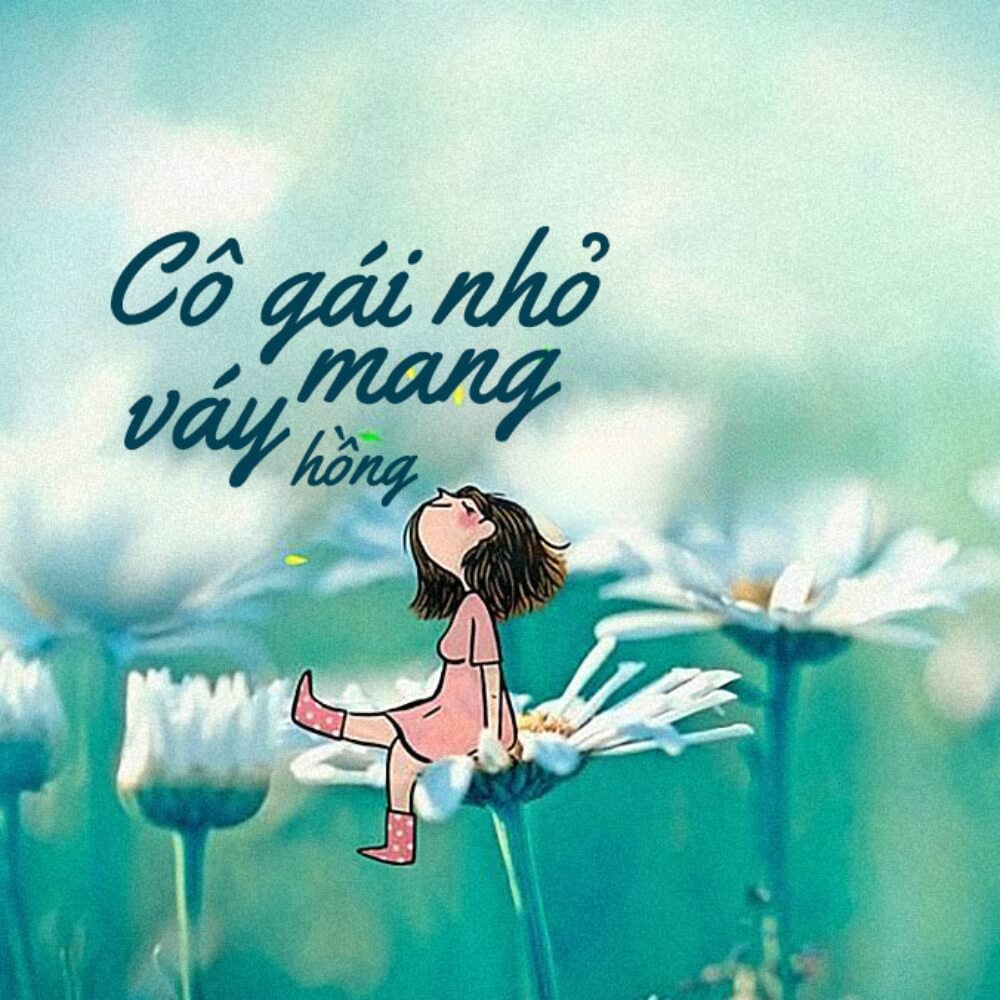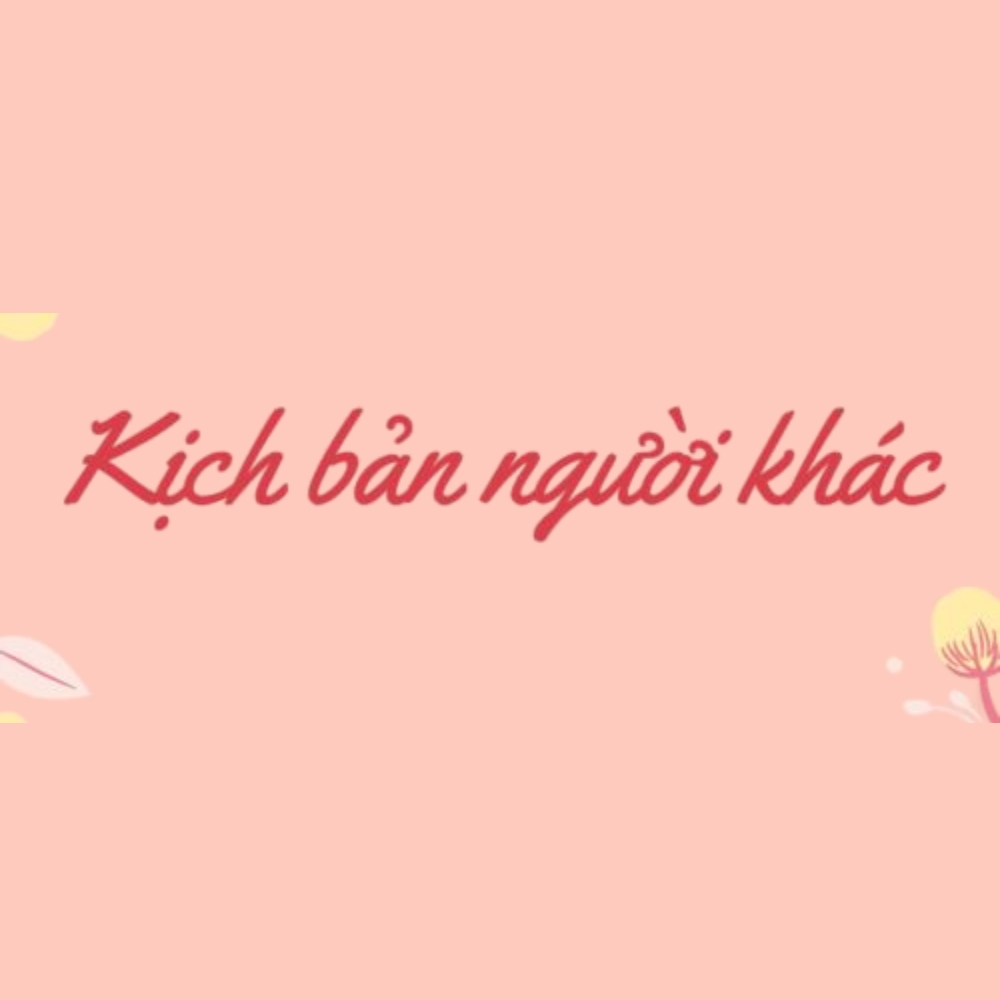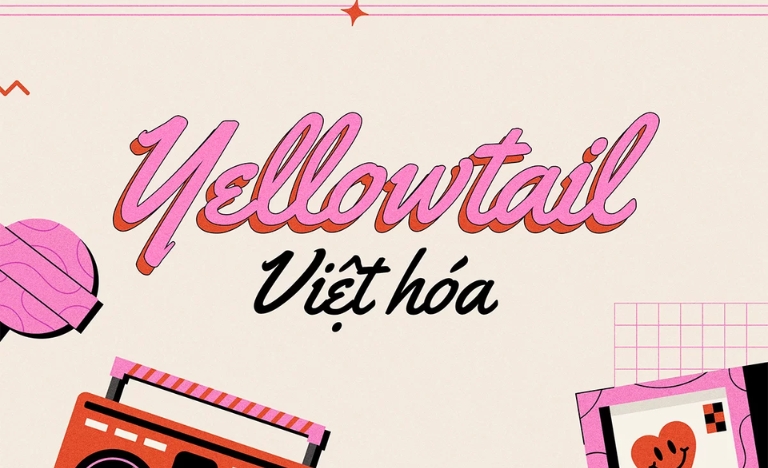
Không ít người khi tìm font Việt hóa Yellowtail thường gặp tình trạng tải về nhưng chữ bị lỗi dấu, thiếu ký tự tiếng Việt hoặc font không hiển thị đúng trong phần mềm thiết kế. Một số file chia sẻ trên internet chỉ là phiên bản chưa việt hóa hoàn chỉnh nên khi sử dụng trong logo, poster hay banner rất dễ bị sai bố cục chữ.
Điều này khiến thiết kế mất đi sự tinh tế và chuyên nghiệp. Trong bài viết này, xưởng In Viva chia sẻ bộ font việt hóa Yellowtail đầy đủ giúp bạn sử dụng dễ dàng cho thiết kế và in ấn.
Trước khi tải font về sử dụng, bạn nên kiểm tra kỹ định dạng file và khả năng hỗ trợ tiếng Việt. Điều này giúp font hoạt động ổn định trên các phần mềm thiết kế phổ biến như Illustrator, Photoshop hoặc CorelDRAW. Dưới đây là thông tin cơ bản của bộ font việt hóa Yellowtail.
| Tên font | Yellowtail |
| Kiểu chữ | Script / Handwriting |
| Hỗ trợ | Tiếng Việt đầy đủ |
| Ứng dụng | Logo, poster, banner, typography |
Bộ font lnth yellowtail việt hóa thường được sử dụng trong các thiết kế mang phong cách chữ viết tay hiện đại. Nhờ nét chữ mềm mại, font này dễ tạo cảm giác tự nhiên và thân thiện trong nhiều loại ấn phẩm.
Đặc điểm nổi bật của font việt hóa Yellowtail
Trong nhóm font script, font việt hóa Yellowtail được nhiều designer lựa chọn nhờ phong cách chữ viết tay thanh thoát và dễ ứng dụng. Khác với nhiều font calligraphy phức tạp, Yellowtail có cấu trúc chữ rõ ràng nên vẫn giữ được tính thẩm mỹ nhưng không gây khó đọc.
Những đặc điểm nổi bật của font việt hóa lnth Yellowtail gồm:
- Nét chữ mềm mại và tự nhiên giống chữ viết tay.
- Khoảng cách chữ hợp lý giúp dễ đọc hơn so với nhiều font script khác.
- Phù hợp cho thiết kế logo, tiêu đề hoặc typography.
- Dễ kết hợp với nhiều font sans-serif trong bố cục thiết kế.
Nhờ những ưu điểm này, tải font chữ lnth yellowtail việt hóa đang trở thành lựa chọn phổ biến với designer khi thiết kế poster hoặc thương hiệu mang phong cách trẻ trung.
Ứng dụng font Yellowtail trong thiết kế và in ấn
Nhờ phong cách chữ viết tay mềm mại, font việt hóa Yellowtail có thể ứng dụng linh hoạt trong nhiều lĩnh vực thiết kế khác nhau. Khi sử dụng đúng cách, font này giúp tạo điểm nhấn tinh tế cho tiêu đề hoặc logo.
Một số ứng dụng phổ biến của font này gồm:
- Thiết kế logo: nhiều thương hiệu sử dụng font script để tạo cảm giác thân thiện và cá tính.
- Poster sự kiện: font Yellowtail giúp tiêu đề nổi bật và thu hút người xem.
- Banner quảng cáo: nét chữ mềm mại giúp tạo cảm giác gần gũi.
- Typography: thường dùng trong các thiết kế quote hoặc artwork.
Trong thực tế, nhiều designer thường kết hợp font việt hóa Yellowtail với font sans-serif để tạo sự cân bằng giữa tính nghệ thuật và khả năng đọc.
03 lưu ý khi sử dụng font Việt hóa Yellowtail
Font script như font việt hóa Yellowtail mang tính trang trí cao, vì vậy designer cần sử dụng đúng cách để tránh làm bố cục thiết kế trở nên rối mắt.
- Không dùng cho đoạn văn dài: font script nên dùng cho tiêu đề hoặc logo.
- Kết hợp với font đơn giản: pairing với sans-serif giúp thiết kế dễ đọc hơn.
- Convert outline trước khi in: giúp tránh lỗi font khi gửi file cho xưởng in.
Những lưu ý này sẽ giúp bạn sử dụng font việt hóa lnth hiệu quả hơn trong các dự án thiết kế.